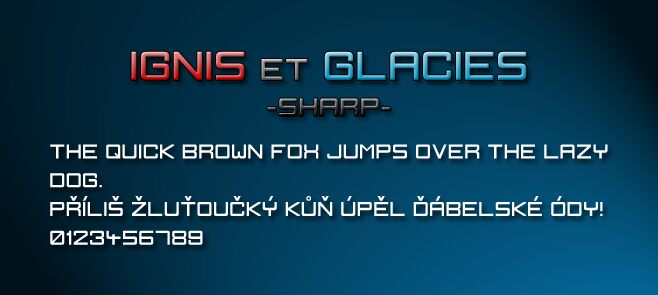
Ignis et Glacies Sharp autorstwa Zdenka Gromnicy to bezpłatny techno krój pisma typu display. Jego masywne, kwadratowe kształty zderzają się z ostro ciętymi przekątnymi, dzięki czemu każde słowo wygląda, jakby zostało wykute w metalu i oświetlone od wewnątrz. Wąskie odstępy i stała grubość kresek tworzą solidną, monolityczną teksturę, która jest czytelna, a jednocześnie sprawia wrażenie eksperymentalnej i nieco agresywnej.
Dzięki Ignis et Glacies Sharp nagłówki nabierają wyrazistości w logo sci-fi, brandingu e-sportowym, na plakatach technologicznych, w tytułach gier, na okładkach albumów i futurystycznych oznaczeniach. Ten darmowy font najlepiej prezentuje się w dużych rozmiarach, gdzie jego ostre rogi i blokowy rytm naprawdę przyciągają wzrok. W tekście głównym warto połączyć go z lekkim, nie rzucającym się w oczy bezszeryfowym krojem, aby uwaga skupiała się na tych odważnych, industrialnych literach.